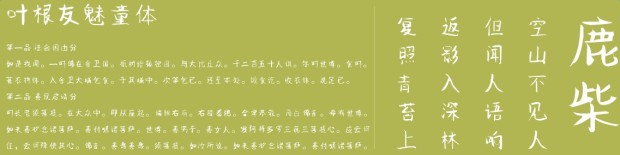
葉根友魅童體字體可以算上一款比較新的字體了,這款字體形態(tài)非常藝術(shù)化,又俏皮可愛(ài),并且是純手寫(xiě)字體哦,感興趣的朋友可以來(lái)綠色資源網(wǎng)下載體驗(yàn)吧!
葉根友魅童體這是一款葉根友字體系列童體風(fēng)格字體。幼稚而頑皮的風(fēng)格穿插于字里行間,“字由字在”的感覺(jué)來(lái)體現(xiàn)中國(guó)漢字的舒展是這款葉根友魅童字體的風(fēng)格追求,純手寫(xiě)體字體,希望大家喜歡。
葉根友魅童字體可愛(ài)俏皮,擁有自己獨(dú)特的感覺(jué),讓現(xiàn)代人有一種新鮮的感覺(jué),為你創(chuàng)造不一樣的字體風(fēng)格,讓你擁有藝術(shù)感的字體!